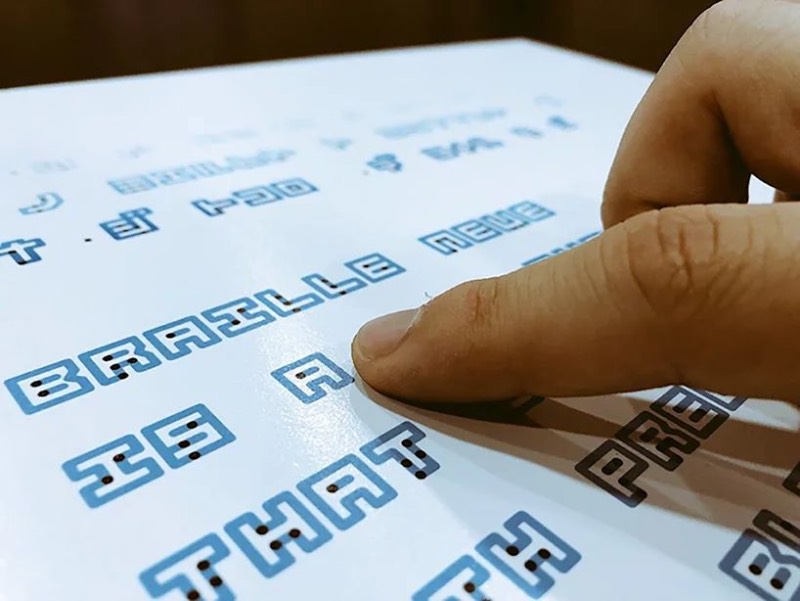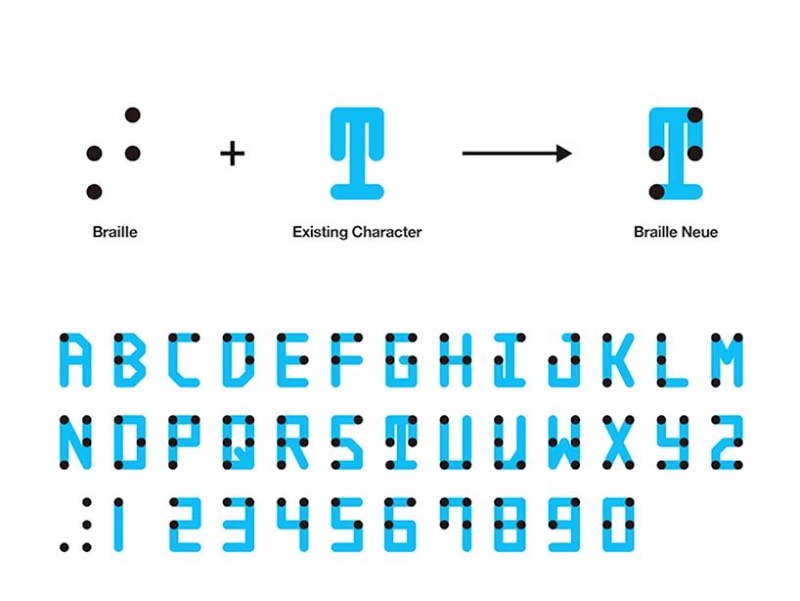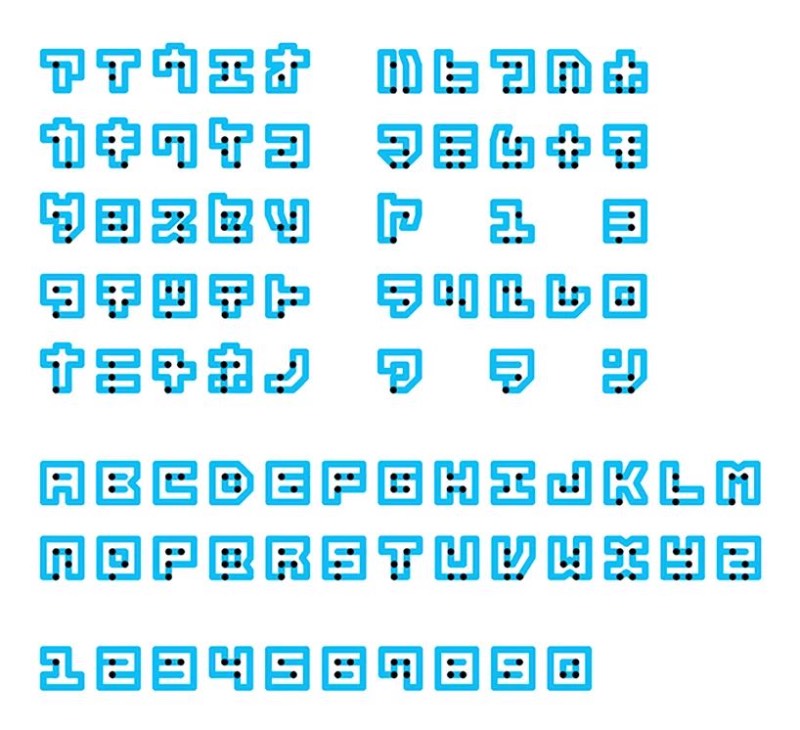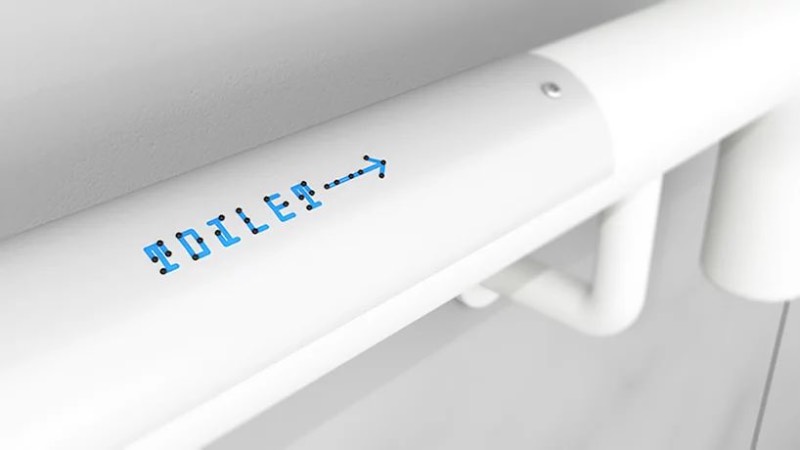
Braille Neue por Kosuke Takahashi
Braille Neue é uma nova fonte criada pelo japonês Kosuke Takahashi que combina o uso do braille com uma tipografia que utiliza de caracteres orientais e outros em latim. A ideia aqui é combinar o uso do braille no dia a dia da tipografia para mostrar ao mundo que existem pessoas que dependem desse tipo de linguagem cinética para navegar pelo mundo.
Para mim, é bem estranho enxergar tipografia combinada com a linguagem em braille. Normalmente quando vejo o braille no meu dia a dia, ele vem quase sempre separado e posicionado de um jeito que fica difícil combinar esse alfabeto com outras coisas. Acredito que, dessa forma que usamos hoje, muitas pessoas acabam nem conectando o braille com uma linguagem e falta um pouco de empatia com quem precisa usar dessa ajuda para se localizar e se informar.
Quando utilizada na sua função esperada, a Braille Neue pode ser vista em uma combinação de linguagens em espaços públicos. Algumas vezes, isso poderia até ser feito sobre os textos que já estão em público. Isso pode acontecer em público pela primeira vez durante a Olimpíada de Tóquio de 2020. Esse é um dos objetivos de Kosuke Takahashi que pretendo criar espaços verdadeiramente universais onde todas as pessoas podem ter acesso a informação da mesma maneira.
Braille Neue foi desenvolvida em duas formas diferentes. Braille Neue Standard é a versão em latim que usa da tipografia que conhecemos e usamos diariamente. Braille Neue Outline usa dos caracteres em japonês junto com os caracteres ocidentais. Algo bem interessante de ser visto como você pode ver no link logo abaixo. Além disso, você pode ver ainda mais sobre essa fonte direto no Product Hunt que foi onde eu me deparei com ela pela primeira vez.
Uma Tipografia Universal chamada Braille Neue por Kosuke Takahashi